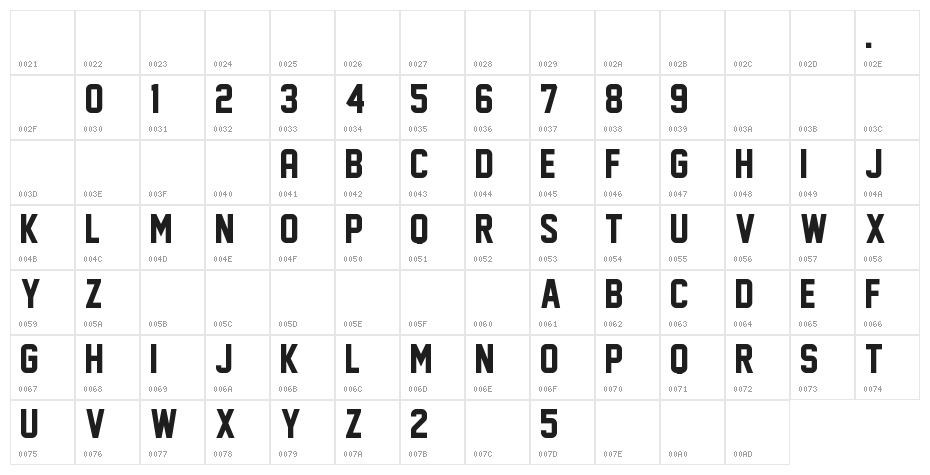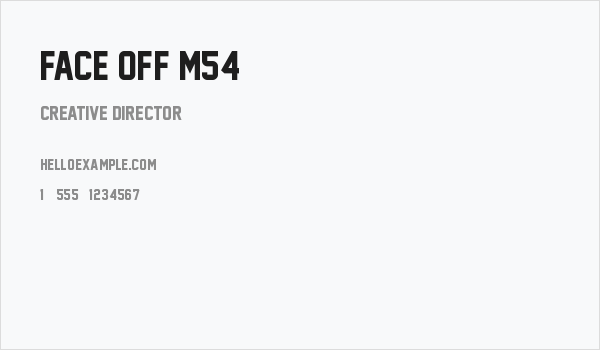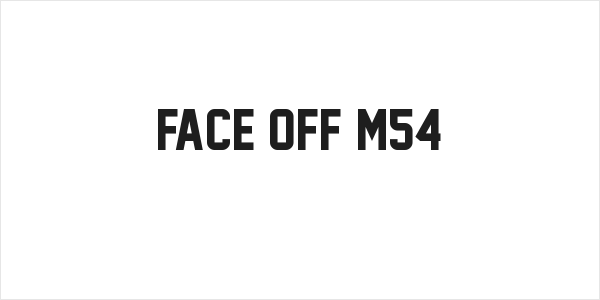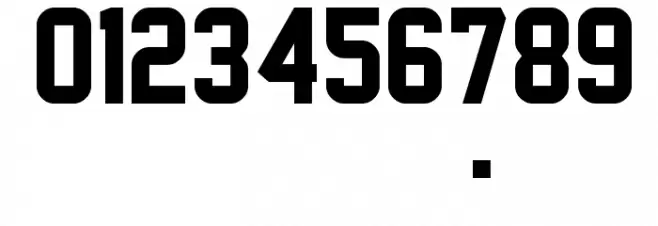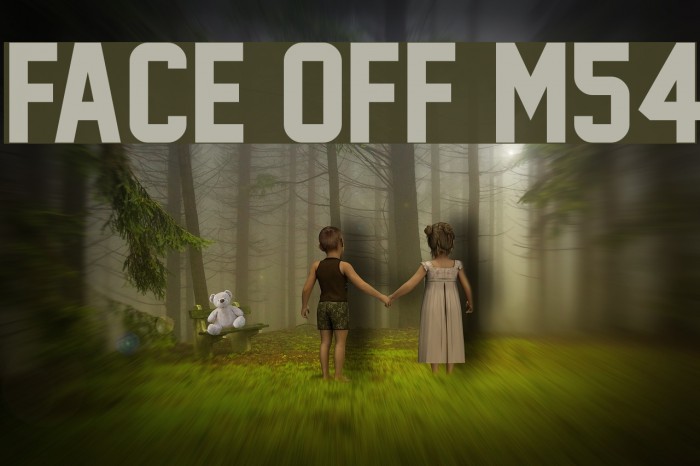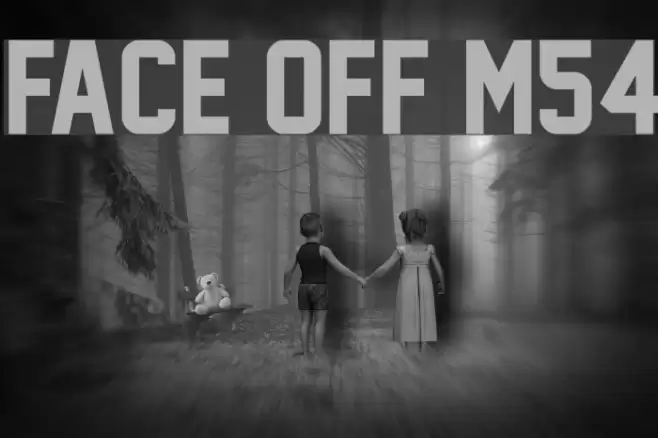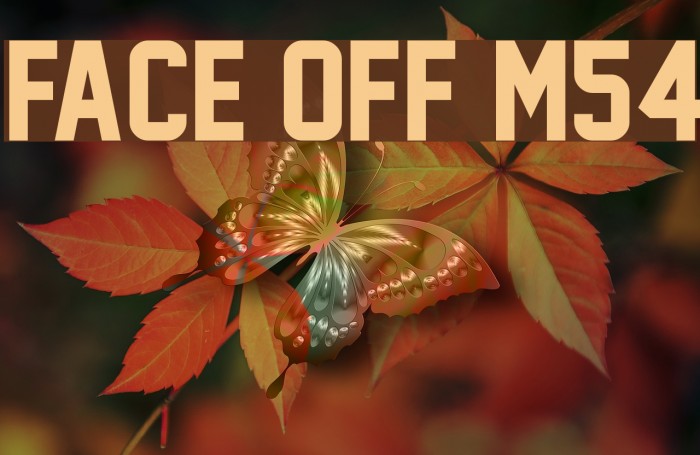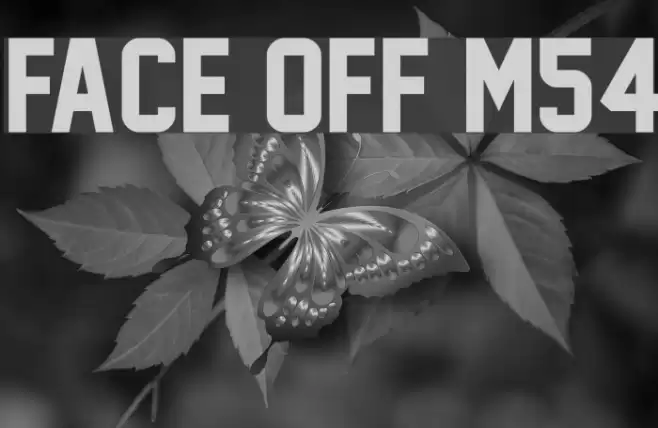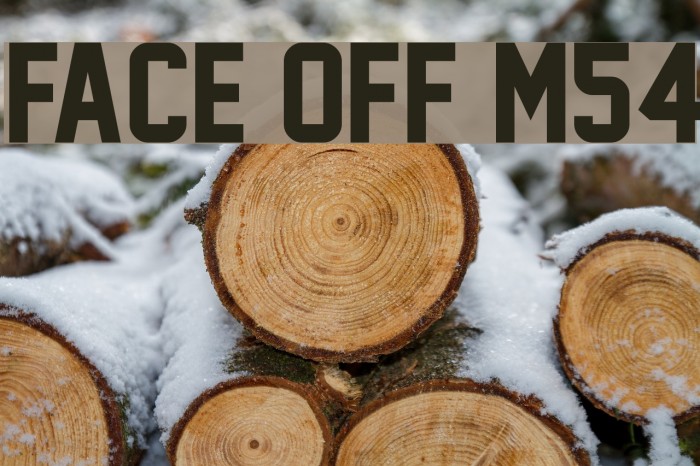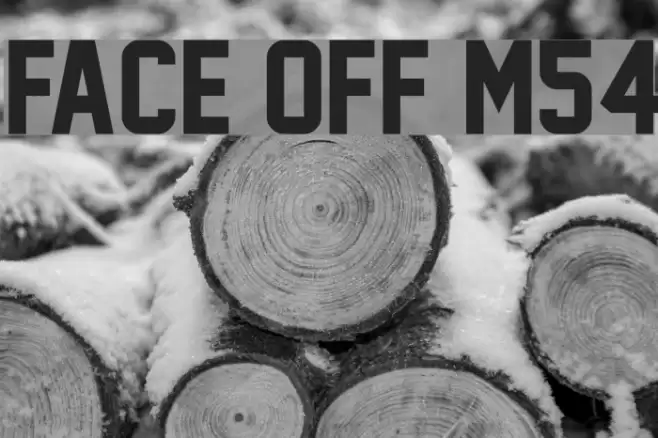
Face Off M54 Font
✎ Thick
| Kategorien | Thick |
| Vorgeschlagene Projekte | Ideal for branding, posters, headlines, and digital media where a strong visual impact is needed. |